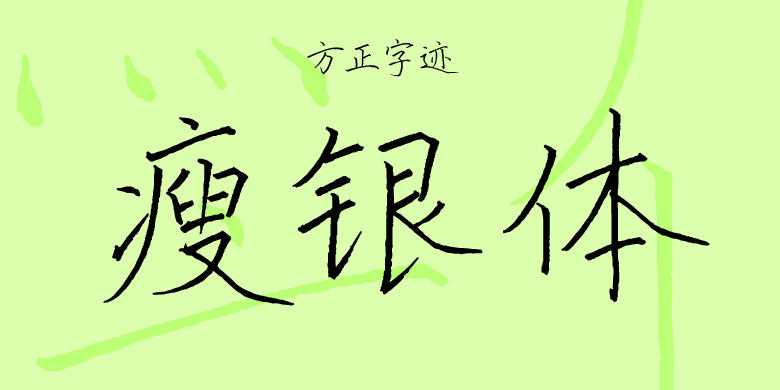
方正字迹-瘦银体
方正字迹-瘦银体,这款字体结构工整、笔画清晰,兼顾美观与易读性,适用于标题、正文、海报、包装、LOGO 等多种场景。字形优雅稳定,风格百搭耐看,适配日常排版与创意设计,让文字呈现更舒适、更具质感。方正字迹-瘦银体一笔一画,皆是细节,以均衡的比例、流畅的线条打造舒适视觉体验,字形端正大气,风格简约现代。无论是商业设计、品牌宣传还是日常排版,都能轻松驾驭,让文字更有格调与力量。方正字迹-瘦银体字体下载。
唐代诗人杜甫有诗云:“书贵瘦硬方通神”,作者用美工钢笔书写楷书字体,笔画相较普通钢笔、签字笔更富于粗细、轻重变化,但又比毛笔字纤细,既瘦劲又挺拔,兼具实用性与艺术性。